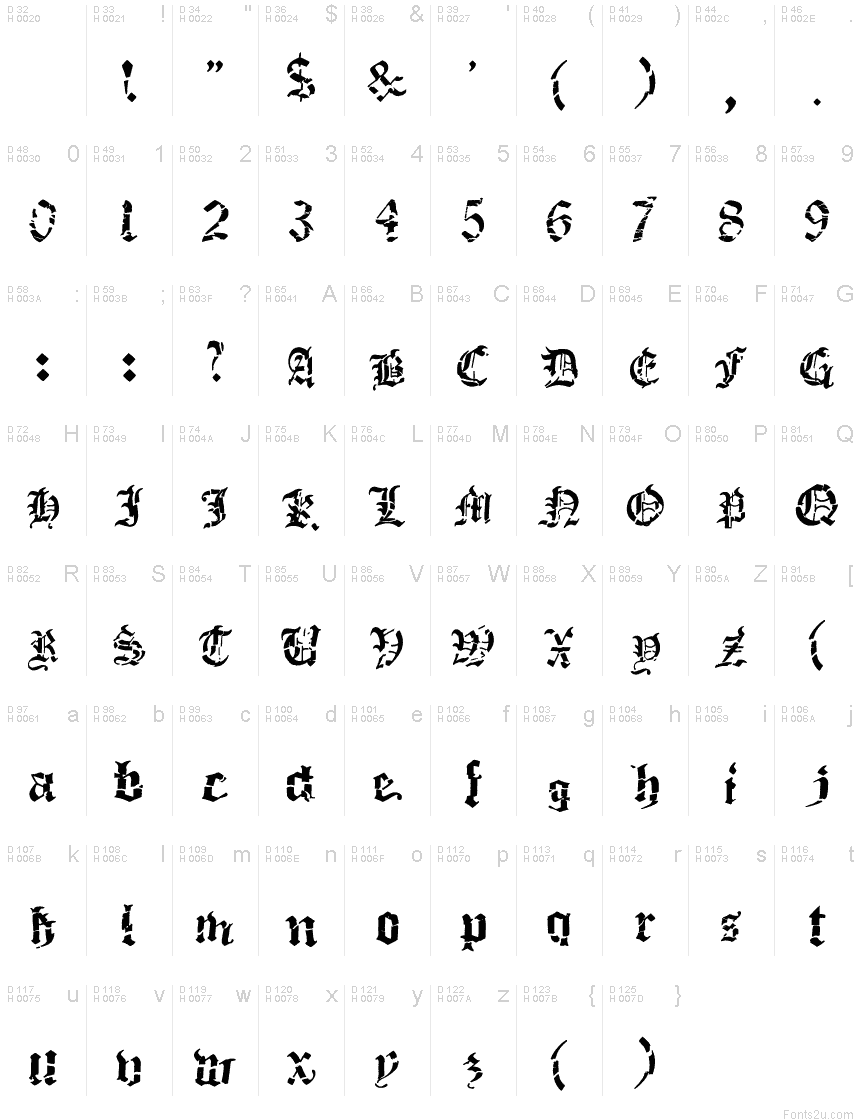
Death Fucking Metal
Death Fucking Metal to darmowy, zniekształcony font displayowy w stylu blackletter, o dzikim i ostrym charakterze. Litery łączą w sobie ciężar średniowiecznego blacklettera z uciętymi rogami, nierównymi łączeniami i ostrymi kolcami – całość sprawia wrażenie bardziej poszarpanego logo zespołu niż grzecznej interpretacji klasyka.
Idealnie pasuje do plakatów, okładek albumów, zinów, ulotek festiwalowych i merchu, wszędzie tam, gdzie tytuł musi oddawać wrogą, undergroundową atmosferę. Jako darmowy font świetnie sprawdzi się też w nagłówkach, krótkich tytułach i surowych monogramach, ponieważ te poszarpane kształty niosą przekaz, zanim jeszcze zaczniesz czytać.